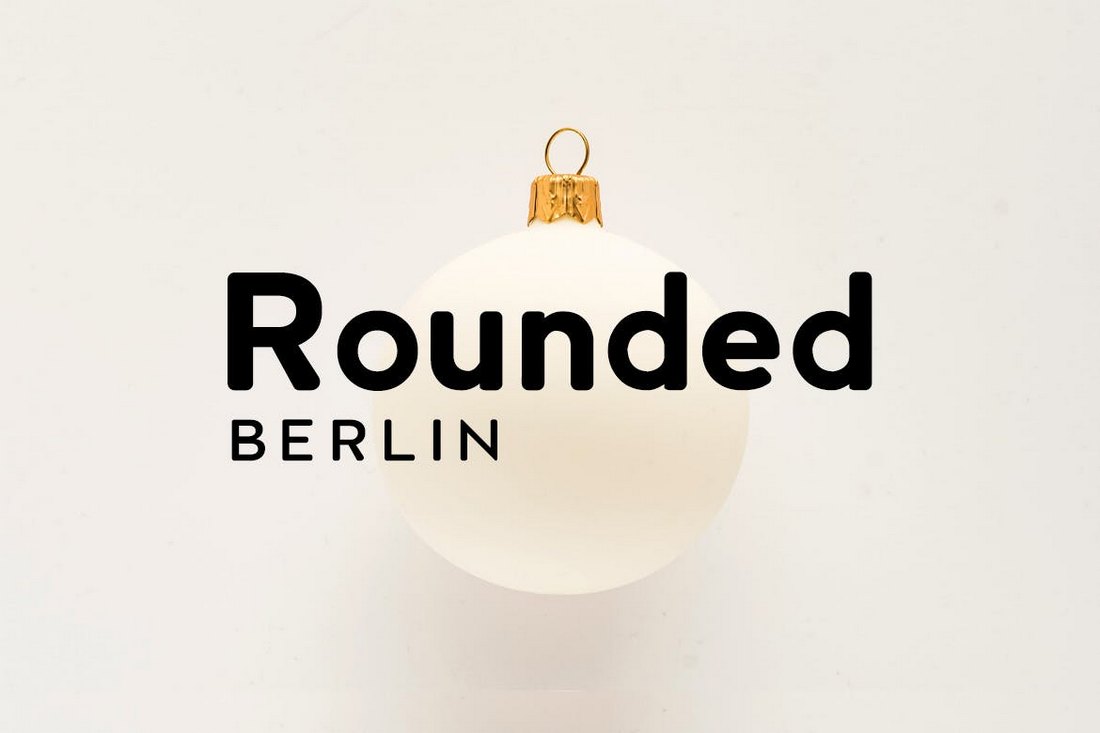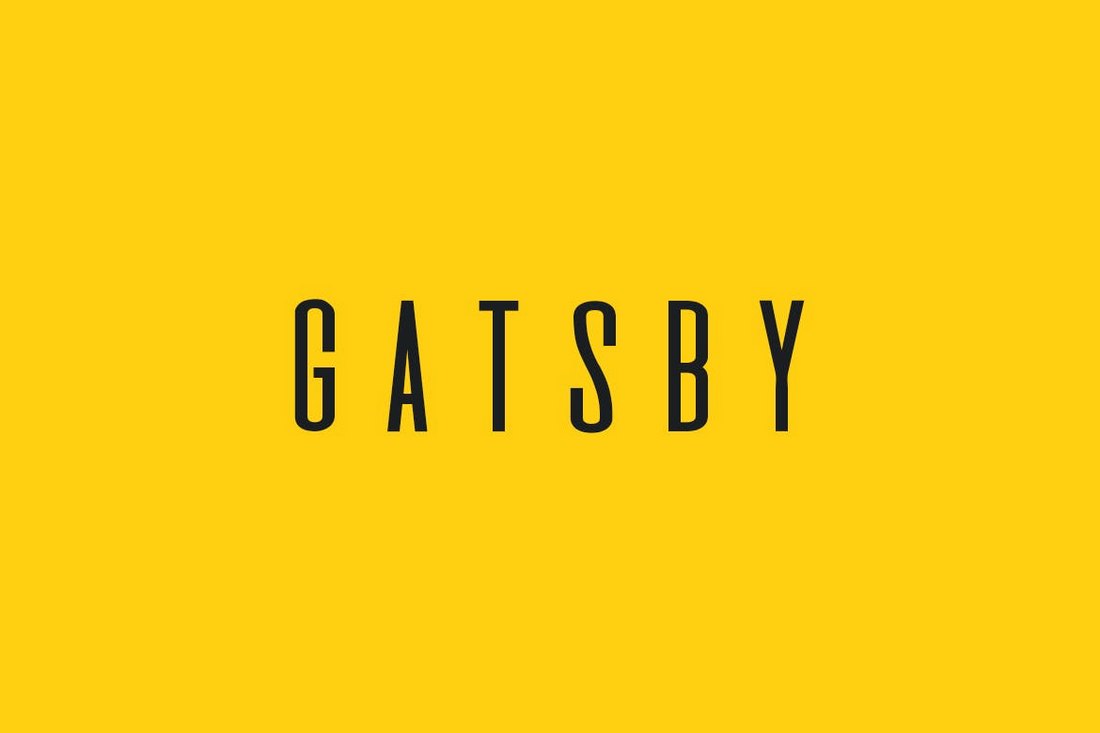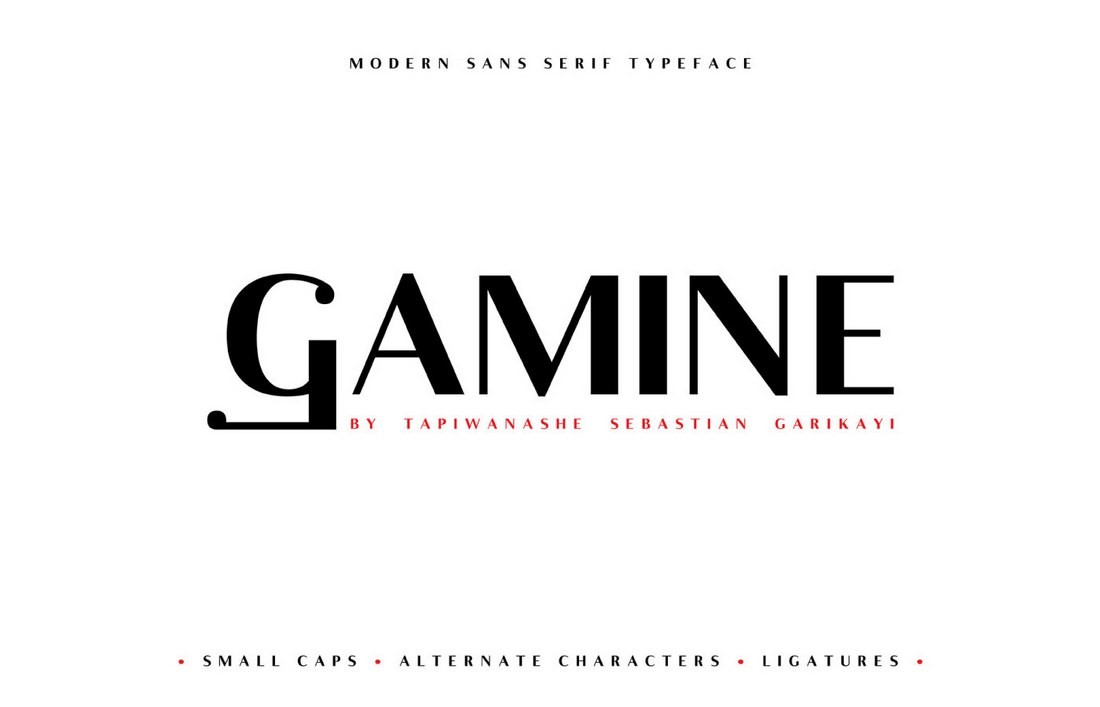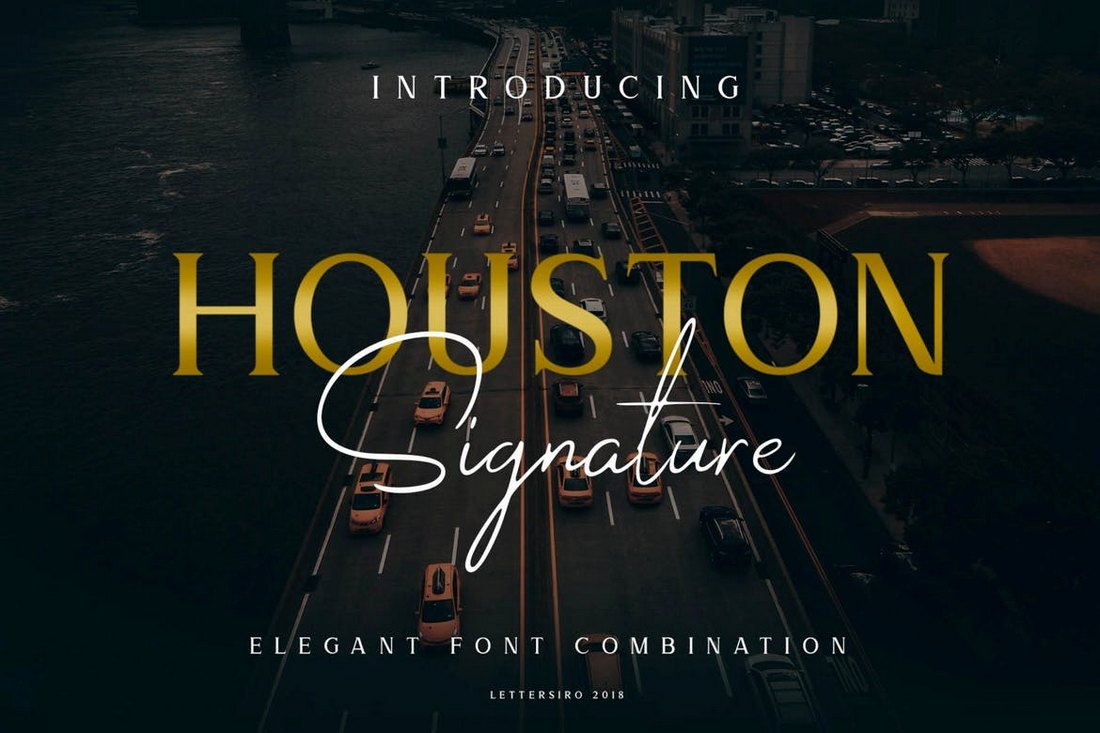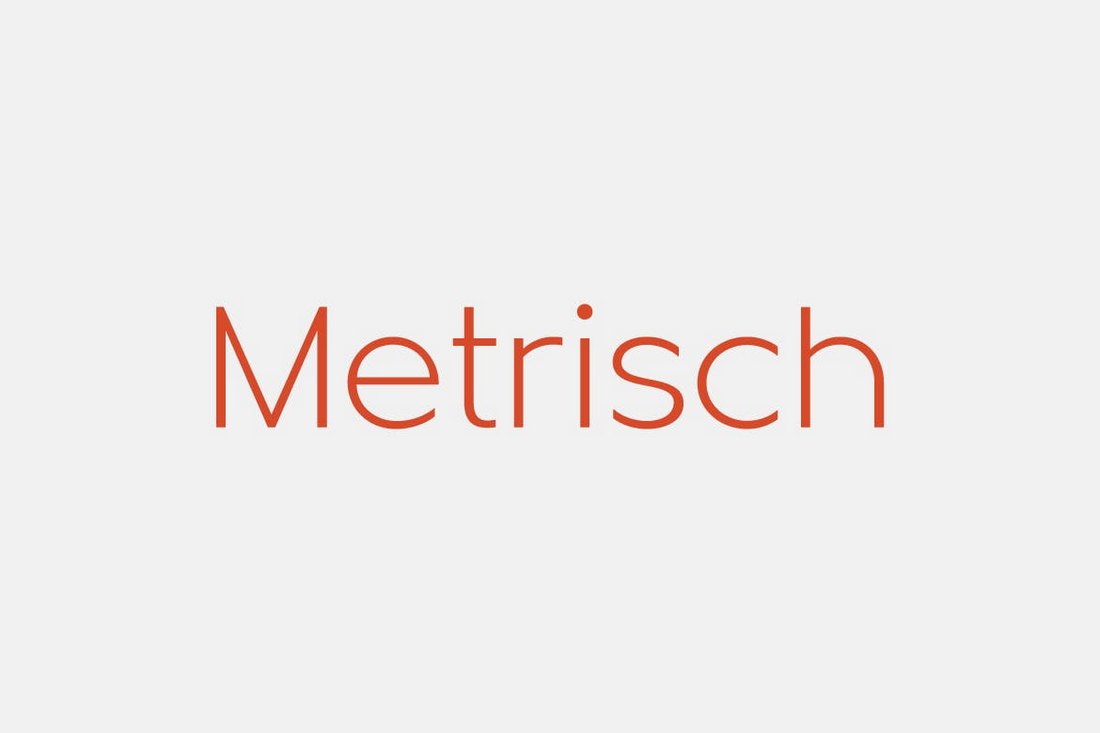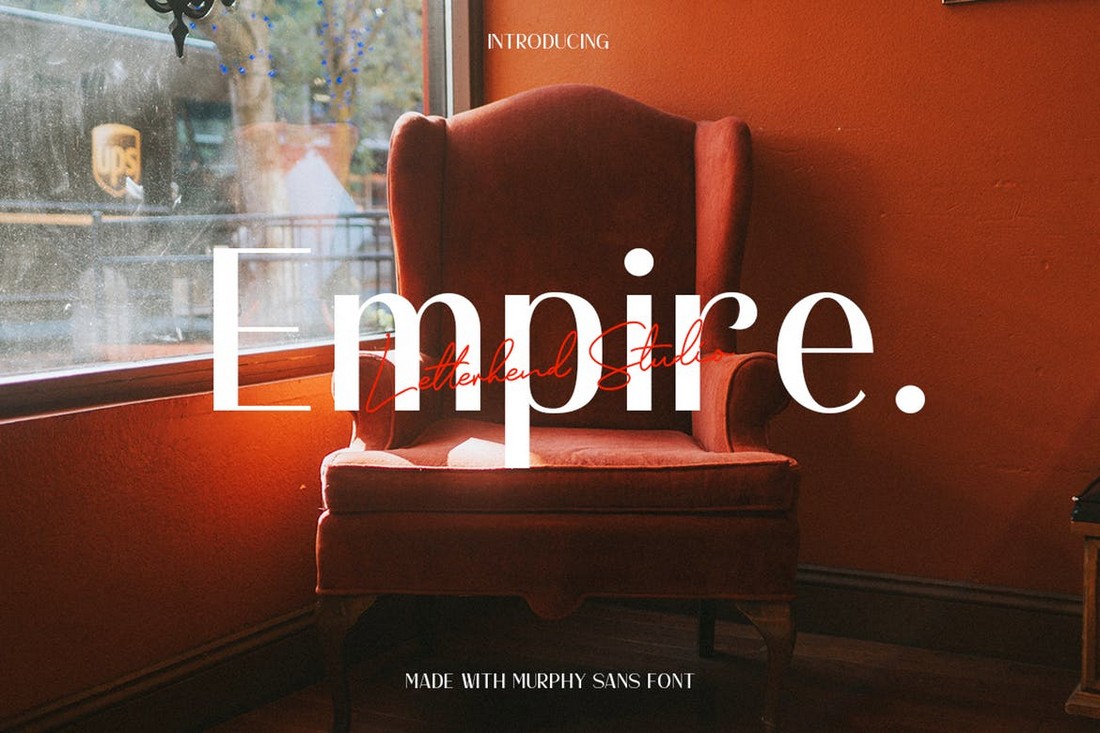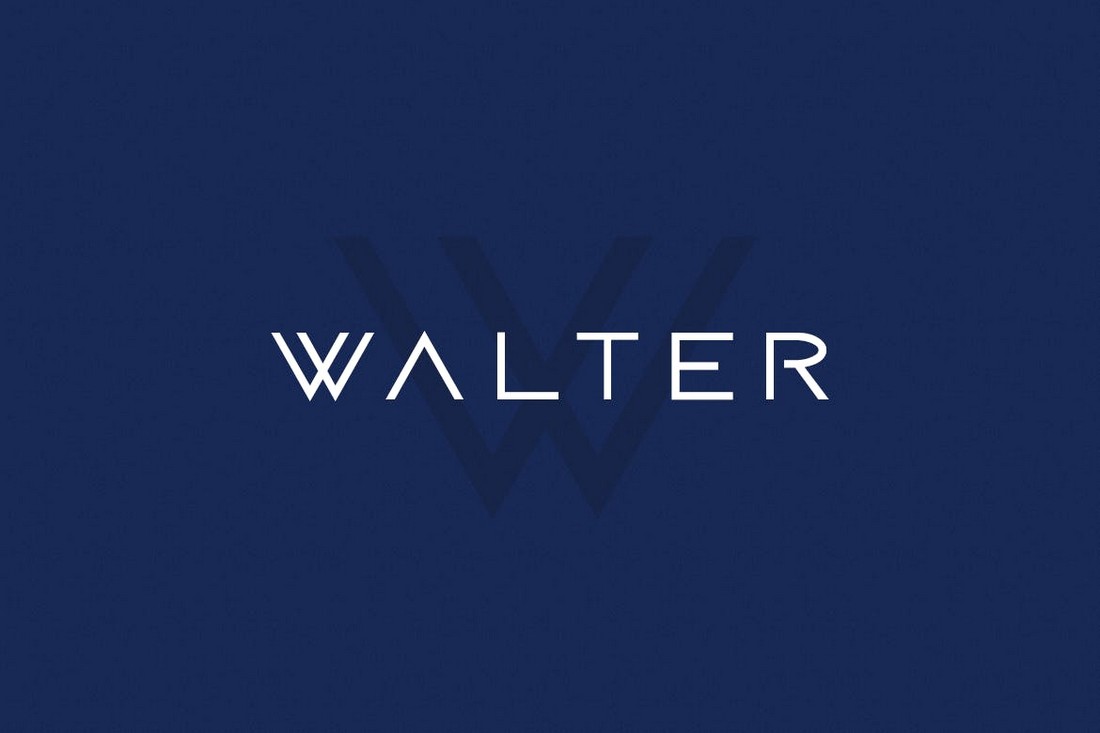
如果你正在尋找徽標,名片,文具或公司業(yè)務(wù)的任何品牌相關(guān)的理想字體,那么今天的內(nèi)容或許可以幫助到你。
在今天的這篇文章中,我們?yōu)槟阏砹艘恍┚x的字體集合,你可以在與商業(yè)和企業(yè)品牌相關(guān)的設(shè)計中使用。
無論你是制作商務(wù)傳單,海報,標牌,還是用于品牌標識,你都可以在我們的系列中找到可用于各種設(shè)計項目和目的的字體。
1.Nordhead – Business & Corporate Font
Nordhead是一款設(shè)計干凈的專業(yè)的字體,可用于設(shè)計各種業(yè)務(wù)和公司相關(guān)的設(shè)計。 包括徽標,名片以及文件抬頭等。 字體的無襯線極簡樣式也為設(shè)計增加了更多的視覺價值。
2.WALTER – Modern Business Font
Walter是一款富有創(chuàng)意的商業(yè)字體,具有獨特的設(shè)計,使其非常適合豪華和高端的品牌設(shè)計。 字體有5種不同的字體粗細(從細到粗),并且提供了可用于像網(wǎng)站設(shè)計的數(shù)字版本。
3.Monolith – Minimal Sans Font Family
Monolith具有極簡主義設(shè)計的字體。 該字體最適合用于現(xiàn)代企業(yè)和創(chuàng)意機構(gòu),可用于制作徽標,名片和網(wǎng)站設(shè)計。 字體包括多國語言支持,并且有多種粗細可供選擇。
4.Murphy Sans – Elegant Business Font
Murphy Sans是一款優(yōu)雅的字體,具有sans-serif設(shè)計,實際上看起來像是襯線字體。 這使其具有獨特的專業(yè)外觀,該字體非常適合制作各種商業(yè)和公司設(shè)計。
5.Gamine – Free Sans-Serif Business Font
Gamine是一款具有獨特字母設(shè)計的免費字體。 字體帶有一組備用字符和連字,可用于為設(shè)計添加獨特的風格。 并且你可以在你的個人和商業(yè)項目中完全免費使用。
6.Houston – Elegant Business Font
Houston是一款優(yōu)雅的商業(yè)字體,同時包含腳本字體和襯線字體,你可以將兩者結(jié)合使用以創(chuàng)建時尚的商業(yè)和企業(yè)設(shè)計。 字體也有細體和傾斜樣式提供。
7.BERLIN Rounded – Sans Serif Font
Berlin是一款精美的無襯線字體,帶有一組經(jīng)過特殊設(shè)計的字符樣式。 該字體非常適合為現(xiàn)代初創(chuàng)企業(yè)和公司制作徽標,橫幅和網(wǎng)站設(shè)計中的標題。 字體有4種不同的粗細。
8.Metrisch – Simple Business Font
Metrisch是一款具有極簡設(shè)計的創(chuàng)意商業(yè)字體。 該字體最適合用于制作專業(yè)和公司相關(guān)的徽標設(shè)計,文具,傳單等。 字體還具有多種可替換的樣式和多個粗細選項。
9.GATSBY – Unique Display Typeface
就像早起經(jīng)典的書籍一樣,這種美麗的字體具有經(jīng)典的復(fù)古設(shè)計,也使其成為創(chuàng)意和代理設(shè)計的絕佳選擇。 字體有4種不同的樣式,包括“普通”,“輪廓”,“復(fù)古”和“變形”。
10.Devant Pro – Modern Business Font
Devant pro是專業(yè)的sans-serif字體,具有粗體和窄字母設(shè)計。 該字體帶有多種字體格式,包括SVG格式。 它是創(chuàng)意網(wǎng)頁設(shè)計,海報和徽標的理想選擇。